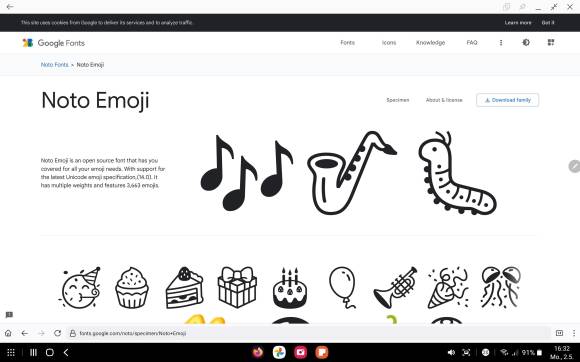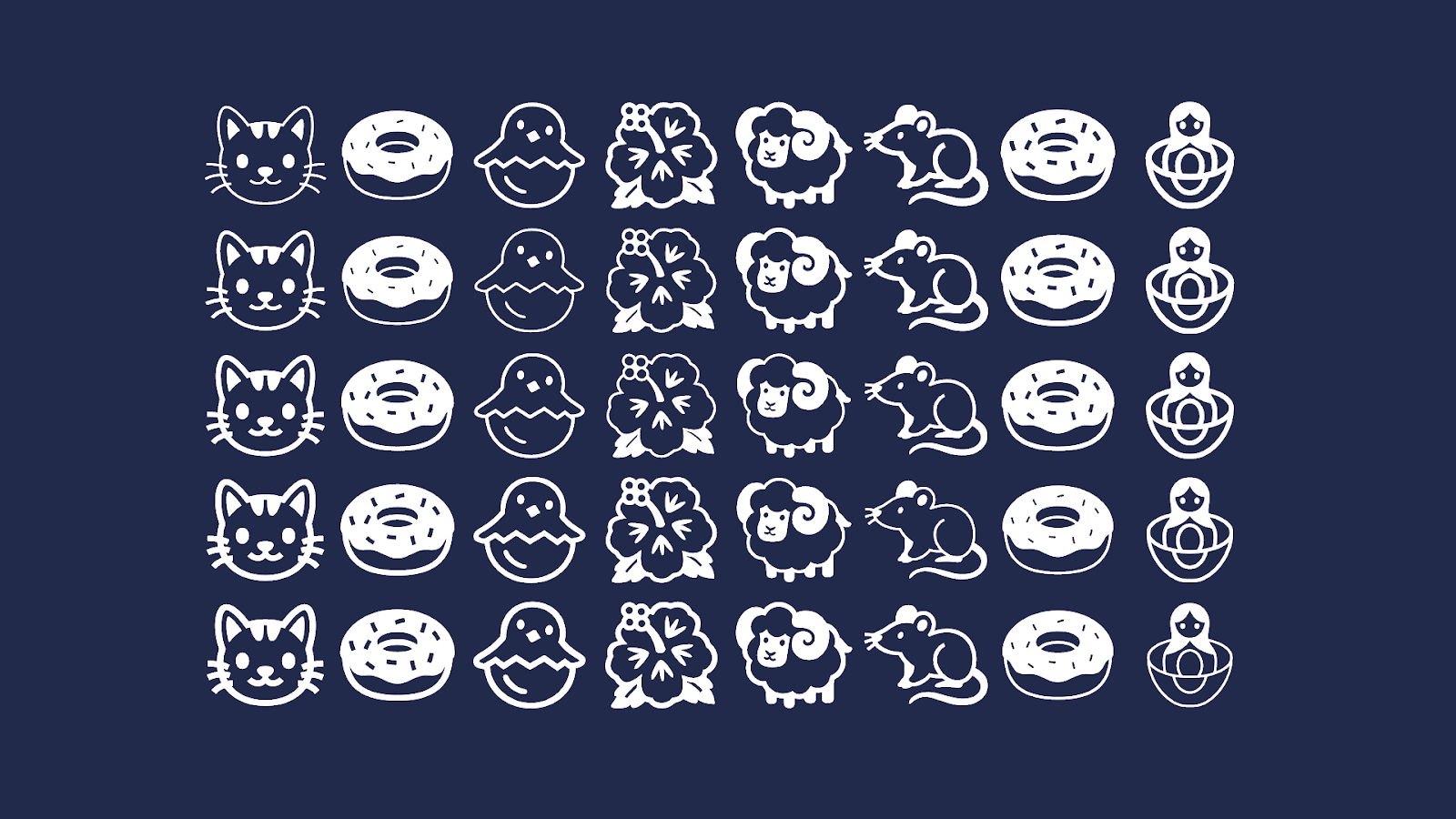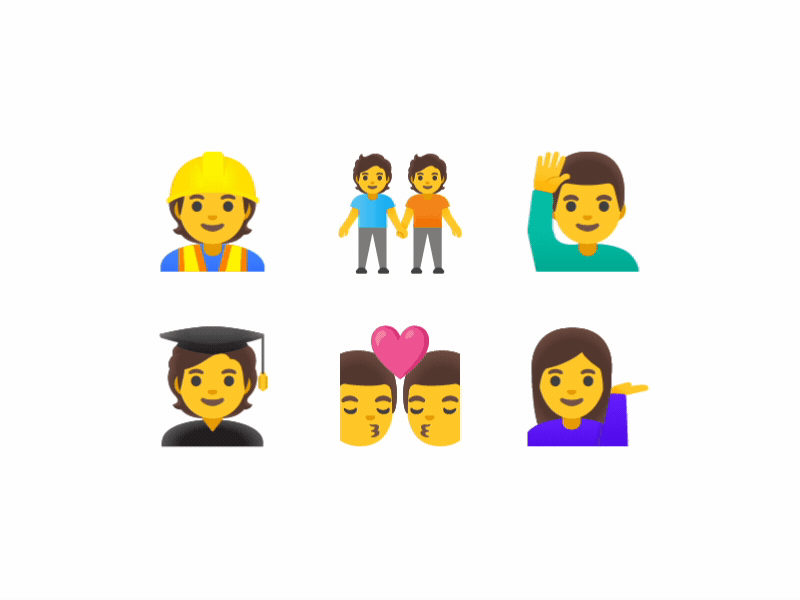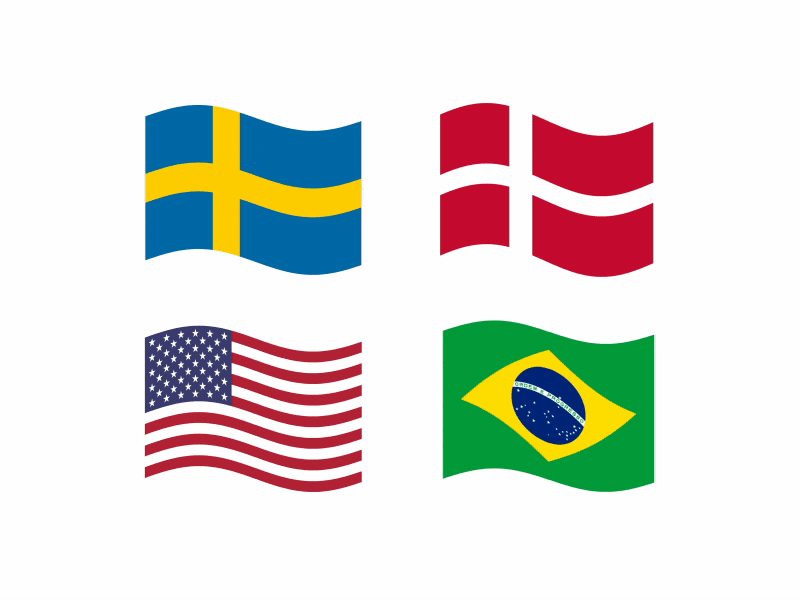
Noto Emoji
Google veröffentlicht neue Emoji-Schriftart
Die Emoji-Schriftart wurde vereinfacht und kommt in schwarz-weiss bzw. einfarbig daher. Auch die Blobs sind wieder mit von der Partie.
Google hat mit Noto Emoji eine einfarbige Emoji-Schriftart lanciert. Noto Emoji ist laut Google-Developer-Blog (engl.) das monochrome Pendant zu Noto Emoji Color. Obwohl die Emojis einfacher wurden, sind sie weiterhin sehr detailliert und gut erkennbar. Nutzerinnen und Nutzer können die Farbe und Grösse individuell ändern. Ausserdem gibt es sowohl einen hellen als auch dunklen Modus, falls Sie z. B. auf Ihrem Smartphone den Dark Mode verwenden. Des Weiteren kann man den Stil anpassen. Die Stufe «leicht» erscheint klein, mit der Stufe «fett» ist ein Emoji markanter.
Auch Landesflaggen wurden vereinfacht. Da man diese in Schwarz-Weiss nicht mehr alle erkennen könnte, hat Google die ISO-Ländercodes verwendet. Durch die Buchstabenfolgen ist klar, um welches Land es sich handelt.
Die Blobs sind wieder da
Sie waren irgendwie niedlich, obwohl sie matschig waren. Sie unterschieden nicht zwischen den Geschlechtern und wirkten sympathisch. Bei der Vereinfachung der Personen-Emojis entschieden die Entwickler, die Blobs wiederauferstehen zu lassen.
Noto Emoji ist Open-Source und unterstützt die neusten Unicode-Emoji-Spezifikationen (14.0). Laut Webseite gibt es momentan 3663 Emojis. Die Emoji-Schriftart können Sie über diesen Link herunterladen.